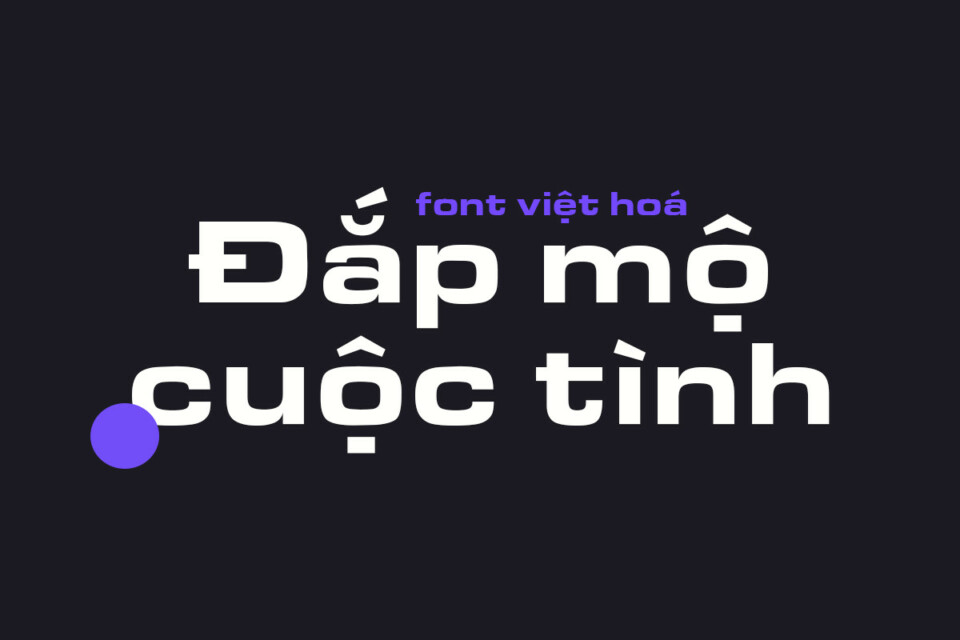
Giới thiệu về Font việt hóa MJ Eurostile Extended
Trong thế giới thiết kế đồ họa hiện đại, việc lựa chọn một bộ Font Chữ phù hợp đóng vai trò then chốt trong việc truyền tải thông điệp. Font việt hóa MJ Eurostile Extended là một phiên bản đặc biệt dựa trên kiểu chữ hình học vuông vức nổi tiếng, mang lại vẻ đẹp mạnh mẽ và chuyên nghiệp. Với đặc tính mở rộng (extended), bộ font này cực kỳ phù hợp cho các tiêu đề lớn, banner quảng cáo hoặc các dự án yêu cầu sự hiện đại, tối giản nhưng không kém phần ấn tượng.
Ưu điểm nổi bật của bộ font MJ Eurostile Extended
Thiết kế hiện đại và linh hoạt
Đặc điểm nhận diện lớn nhất của Font việt hóa MJ Eurostile Extended chính là cấu trúc khung chữ hình chữ nhật bo góc, tạo cảm giác công nghệ và tương lai. Phiên bản việt hóa đã được tinh chỉnh kỹ lưỡng các dấu câu để đảm bảo hiển thị mượt mà trên mọi trình soạn thảo văn bản. Điều này giúp các bạn học sinh và giáo viên dễ dàng ứng dụng vào bài thuyết trình hoặc làm tư liệu giảng dạy sinh động hơn.
Ứng dụng đa dạng trong thực tế
Bộ font này không chỉ dành cho dân chuyên nghiệp mà còn rất gần gũi với đời sống học đường. Bạn có thể dùng nó để thiết kế bìa báo tường, làm thiệp mời sự kiện trường học hoặc trình bày các báo cáo khoa học. Khả năng đọc tốt ở kích thước lớn giúp người xem dễ dàng tiếp nhận thông tin từ xa, tạo nên sự hài hòa tuyệt đối cho bố cục tổng thể.
Kết luận và cách sử dụng hiệu quả
Sở hữu Font việt hóa MJ Eurostile Extended sẽ giúp bạn nâng tầm thẩm mỹ cho mọi sản phẩm sáng tạo. Để có kết quả tốt nhất, hãy kết hợp nó với các font chữ không chân mảnh để tạo độ tương phản. Nếu bạn đang tìm kiếm những bộ Font Miễn Phí, Font Việt Hóa, Font việt hóa MJ Eurostile Extended chất lượng, đây chắc chắn là lựa chọn hàng đầu không thể bỏ qua trong năm nay.